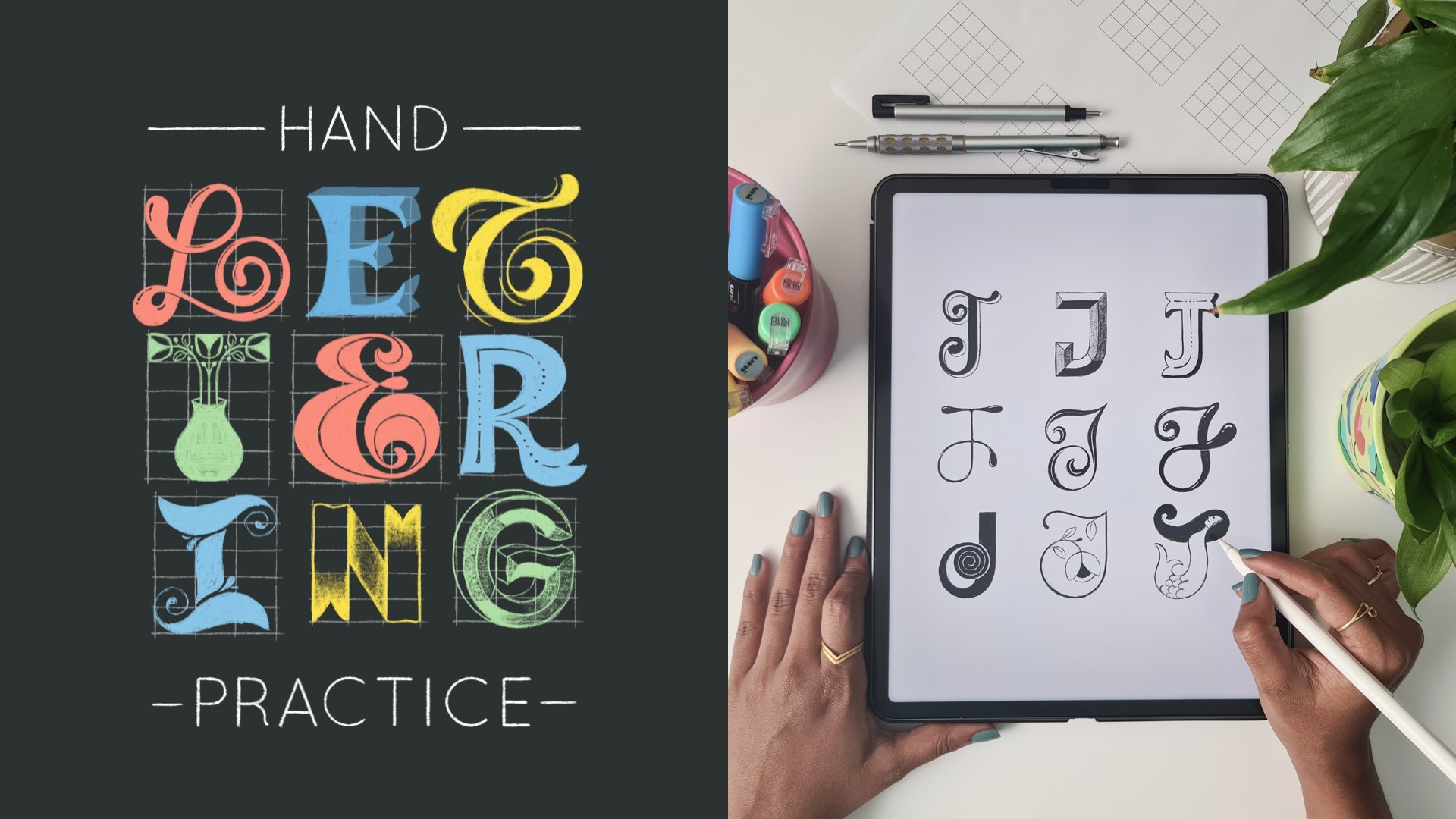
Prática de lettering à mão: 3 passos fáceis para explorar novos estilos de tipografia
As letras são como nós. Elas vêm em todos os tipos de formatos, formas e até personalidades!
E se eu dissesse que você pode desenvolver seus próprios estilos de lettering exclusivos do zero através de prática e exploração?
Neste curso, ensinarei como desenvolver estilos de lettering através de uma abordagem estruturada usando o meu processo em 3 passos para criar letras. Guiarei você por meio desses passos detalhadamente e mostrarei exatamente como uso eles para desenvolver vários estilos de uma única letra.
Tudo que você precisa fazer é usar essa fórmula que ensino para praticar e desenvolver seus próprios estilos de tipografia únicos, um caractere de cada vez.
A prática diária focada é a única coisa que levará você a um novo nível em sua jornada de lettering. Na minha opinião, não existe uma quantidade de dicas e truques que substituirá o que a prática pode fazer por suas habilidades. No entanto, pode ser difícil saber como abordar suas sessões de prática para poder aproveitá-las ao máximo. E é isso o que este curso resolve para você.
Neste curso, você aprenderá:
• O que um “estilo de lettering” realmente significa.
• Como praticar o desenvolvimento de letras em uma abordagem organizada e estruturada.
• Como dividir o desenvolvimento do seu lettering nos seguintes pequenos passos:
• Proporções
• formas
• Detalhes
• Como guias de diferentes proporções afetam os tipos de fontes e como aproveitar isso durante sua exploração.
• Melhores práticas e dicas para criar letras e números visualmente equilibrados.
Além disso, você construirá uma grande biblioteca dos seus próprios estilos de lettering que poderá consultar em projetos futuros. Ainda, você pode assistir todo o meu processo de desenvolvimento de nove variações diferentes de uma única letra do início ao fim. Será como sentar ao meu lado no meu estúdio enquanto me perco em minhas letras!
• Arquivos de modelo (disponíveis para download na seção Recursos)
Estarei demonstrando minhas técnicas desenhando no meu iPad usando o aplicativo de desenho Procreate e um Apple Pencil. No entanto, você pode me acompanhar usando qualquer meio de desenho da sua escolha — não é preciso usar um iPad para fazer este curso.
1. Introdução: [MÚSICA] As letras são como nós, elas vêm em todos os tipos de formas, tamanhos e até personalidades. E se eu dissesse que você tem a capacidade de desenvolver seus próprios estilos de letras únicos do zero para a prática e exploração. Sou Vinitha Mammen, uma artista e ilustradora de letras freelancer com formação em design de moda, e uma professora de topo no Skillshare. Nesta aula, ensino-vos a desenvolver estilos de letras por meio uma abordagem estruturada usando meu processo de três etapas de construção de letras. Vou levá-lo por essas etapas em detalhes e mostrar exatamente como as coloco para usar para desenvolver vários estilos de uma única letra. Tudo o que você precisa fazer é usar essa fórmula que eu ensino você a praticar e desenvolver seus próprios estilos de letras únicos, um personagem de cada vez. Trabalhar diariamente em direção a um objetivo específico me ajudou mais do que qualquer outra coisa na minha jornada de letras e ilustrações. Ao longo desses desafios diários, meu próprio estilo de letras único começou a se revelar de maneiras diferentes e isso me deu um senso de direção para avançar. Então, se você aceitar esse desafio, tenho certeza que ele lhe apresentará algumas revelações que mudam a vida ao longo do caminho. Ao final desta aula, você terá um método organizado e estruturado para praticar e explorar suas letras. Se você concluir seus projetos, você terá uma enorme biblioteca de referência de seus próprios estilos de letras que você pode usar em seus projetos futuros. Esta classe é para qualquer pessoa que queira aumentar o nível seu jogo de letras e é adequada para todos os níveis de habilidade. Se você é um iniciante que não sabe como começar, ou já é um artista de letras de nível intermediário ou avançado procura alguma variedade autêntica em seu estilo, eu te cobriu. Vou demonstrar minhas técnicas esboçando no meu iPad usando o aplicativo de desenho Procreate e um lápis Apple. No entanto, você pode acompanhar comigo usando qualquer meio de esboço de sua escolha. Você não precisa ter um iPad para fazer essa aula. Então você está pronto para soltar e fazer alguns exercícios de letras que mudam a vida comigo? Vamos começar. [MÚSICA] 2. Projeto do curso: [MÚSICA] Nesta aula, vamos explorar diferentes estilos de letras através da prática, então seu projeto com essa aula é exatamente isso, prática. Você vai explorar nove variações diferentes de cada letra maiúscula no alfabeto inglês e números de 0 a 9, então isso é 36 ao todo. Para isso, juntei alguns modelos de prática com guias de letras, para que você possa explorar diretamente sem ter que fazer todas as coisas chatas. Fazer todos esses 36 personagens de uma só vez será cansativo e até frustrante, então minha sugestão é que você enfrente apenas um ou um máximo de dois por dia. Dessa forma, você ficará menos sobrecarregado e poderá se aproximar de cada um com uma mente nova. Você pode usar qualquer meio com o qual você se sinta mais confortável para esboçar, você pode usar os modelos digitais para desenhar no seu iPad ou nos modelos imprimíveis, se quiser praticar tradicionalmente com caneta ou lápis em papel. Antes de seguir em frente, faça o download desses modelos de prática na seção de recursos e mantenha-os à mão. À medida que você progride em sua prática, você pode fazer upload de imagens e vídeos de suas explorações na galeria do projeto, para que todos possamos nos inspirar trabalho um do outro e nos manter e uns aos outros responsáveis. Também farei esse projeto e estarei enviando minhas folhas de prática na galeria do projeto, bem como no Instagram. Se você optar por compartilhar sua jornada de prática no Instagram, não se esqueça de me marcar em suas postagens, histórias e reais para que eu possa ver e compartilhar seu trabalho. Dito isso, eu não quero que você se preocupe em compartilhar seu trabalho enquanto explora. A pressão de compartilhar seu trabalho às vezes pode realmente atrapalhar sua solta e se isso é algo que o incomoda, e eu quero que você saiba que você absolutamente não tem que compartilhar seu trabalho. Claro, adoraríamos ver o que você inventou, mas o mais importante aqui é que você explore sem se limitar de forma alguma. Você pode muito bem terminar cada personagem e depois decidir se você quer compartilhar ou não, legal? Da mesma forma, não se preocupe alcançar linhas e curvas perfeitas toda vez ou se você estiver usando o Procreate sobre como seus ajustes afetarão seu vídeo de lapso de tempo, também você pode usar sua borracha tanto ou tão pouco quanto quiser. Tudo o que eu quero é que você deixe perder, confiar no processo e se divertir [MÚSICA], então vamos? Na próxima lição, vou orientá-lo pelo meu processo de três etapas de chegar a diferentes estilos de letras. [MÚSICA] 3. Processo de três etapas: [MÚSICA] O que exatamente queremos dizer quando dizemos estilo de letras? Existem muitos fatores diferentes que entram na definição de um estilo de letras específico. O tipo de letra, os ângulos, o humor, o peso das linhas, os elementos detalhados e muito mais. Todos eles contribuem coletivamente para um estilo de letras específico. Quando tentamos criar novos estilos, temos um monte de coisas para pensar, e se tentarmos enfrentá-los de uma só vez, estaremos por todo o lado. Em vez disso, dividimos isso em um processo simples de três etapas para que tenhamos uma abordagem mais estruturada para desenvolver estilos de letras e podemos nos concentrar em uma coisa de cada vez. Deixe-me dar um pequeno vislumbre desse processo. Primeiro, estabelecemos as proporções de nossos personagens definindo guias para desenharmos. Em segundo lugar, exploramos e chegamos às formas que formam nossas letras. Na etapa final, adicionamos detalhes para encerrá-lo. Falarei sobre cada uma dessas etapas em detalhes nas próximas lições. Por enquanto, tudo o que você precisa lembrar é proporções, formas, detalhes, nessa ordem. Na verdade, é um erro comum de novato, não apenas com letras, mas com qualquer tipo de desenho, ficar preso nos detalhes imediatamente, acabando com peças que estão fora de proporção ou falta de equilíbrio visual. Em vez disso, se você começar estabelecendo uma base sólida antes refinar as coisas e adicionar os detalhes, terá uma chance muito melhor acabar com um esboço bem equilibrado. Na próxima lição, vamos dar uma olhada boa e detalhada em nosso primeiro passo, proporções. [MÚSICA] 4. Passo 1: proporções: [MÚSICA] Como vimos na lição anterior, a primeira coisa em que nos concentramos em nosso processo de três etapas são proporções. Vamos dar uma olhada em como as proporções afetam os estilos de letras e como podemos jogar com eles para criar letras únicas. Agora, de um modo geral, a maioria das nossas letras maiúsculas e números cabem bem dentro de uma grade de cinco por três. Existem algumas exceções às quais chegaremos daqui a pouco, mas, por enquanto, vamos ver como isso funciona. Tenho uma grade de cinco por três aqui. Vamos tentar usá-lo para desenhar algo simples como um E. Com letras como essa, você só precisa seguir as diretrizes e preencher os quadrados apropriados em sua grade. É muito simples. mesmo com outras letras de linha reta como T, H e assim por diante. Agora, se você quiser fazer uma letra mais curvilínea, S , por exemplo, as partes mais arredondadas das curvas escolherão um pouco para fora das guias. Não tente encaixá-los perfeitamente dentro dos guias. Eles ficam melhores quando se estendem para fora do tad. Como você pode ver, elas não são tão diretas quanto as letras de rua, mas uma coisa que ajuda é realmente usar a grade para se concentrar em pequenas seções de cada vez. Uma vez que você pegue um jeito, não será mais um grande negócio. Pratique para chegar lá. Essa é a única maneira. Agora eu tenho as partes superior e inferior. Em seguida, conectamos os dois derrubando isso assim, trazendo isso assim. Agora só precisamos seguir essa curva e desenhar uma curva paralela para essa curva. Da mesma forma aqui, você deseja desenhar uma curva paralela a essa curva. Vamos apenas derrubar o N e depois um pouco assim e fechá-lo. Isso surge assim e, novamente, feche-o. Veja que você ainda está usando essas linhas de grade para guiar suas curvas. Só que você precisa obter suas curvas para se estender um pouco para fora da grade para obter uma forma suave e equilibrada. Quando você o coloca ao lado das outras letras, as curvas são esmagadas na grade, elas não parecerão coesas juntas. Eu vou apenas preenchê-los também para que você possa ver a forma melhor. [MÚSICA] Agora, você pode usar essa grade, não apenas para letras, mas também para números. Vamos tentar um, como sete, por exemplo. É assim que eu faria um sete com uma linha inclinada como esta e uma linha reta no topo. Muito fácil. Agora, até agora, usamos uma grade de cinco por três com colunas e linhas de igual largura. Esta e esta são a mesma largura e é mesmo por toda parte. Agora, podemos tentar mudar isso. Por exemplo, dessa forma podemos mantê-lo o mesmo, mas ao longo desse lado podemos aumentar a largura. Vamos fazer seis em vez de três. Dois, três, quatro, cinco, seis. Vou completar o retângulo. Agora, em vez de desenhar cada linha, vamos desenhar todas as outras linhas para que ainda tenhamos três colunas. É apenas duas vezes mais largo agora. Ainda são cinco por três, apenas com proporções diferentes. Agora vamos tentar usar esse cara para participar do E. O processo é exatamente o mesmo que fizemos antes. Veja, apenas variando as proporções da grade, temos uma aparência diferente E. Da mesma forma, podemos tentar todas as variações diferentes nas proporções. Por exemplo, vamos fazer um do outro lado. Em vez de cinco quadrados para baixo, faremos 10. Dessa forma, vamos voltar para apenas três. Agora nossas colunas são todas de um quadrado largura e nossas linhas terão dois quadrados de largura. Vamos desenhar nosso E nesta nova grade. [MÚSICA] Lá temos mais uma variação do E e você pode ficar ainda mais louco com isso. Vamos tentar alguma coisa. Começaremos com um retângulo de cinco por três, assim como o nosso original. Agora, em vez de dividir isso igualmente em linhas e colunas, podemos até dividi-lo de forma desigual. Em vez de desenhar uma linha no primeiro quadrado, desenhamos um pouco mais alto. Da mesma forma aqui, vamos um pouco mais baixo. Para nossa linha do meio também, podemos entrar um pouco para dentro. Esses três são quase da mesma largura e os dois intermediários são mais grossos e vamos ficar com colunas de igual largura por enquanto. Esta também é uma grade de três por cinco, mas com robôs variados. Agora vamos ver como nosso E parece nesta grade. É semelhante ao primeiro, mas ainda é um pouco diferente. Assim, você pode brincar e criar todas as variações nas proporções da grade, chegar a letras com proporções diferentes. Estou tentando outro aqui com linhas mais grossas na parte superior e inferior. Isso me dá um E que se parece com isso. Em seguida, vou começar com um quadrado aleatório como este e vamos ver o que acontece se dividirmos apenas a linha superior em duas e mantivermos as outras quatro linhas um quadrado de largura. Mais uma vez, temos cinco linhas e vou completamente aleatório com as larguras da minha coluna. Só estou experimentando aqui indo completamente aleatório. Isso é o que isso me dá. Vou tentar mais um que seja extra largo, com uma linha do meio muito magra. Foi isso que acabei usando essa grade. É aqui que a proporção realmente entra em jogo. É assim que variamos as proporções de nossas letras variando as proporções dos próprios guias. Como você pode ver, as possibilidades das diferentes proporções às quais você pode chegar são praticamente infinitas. Quero encorajá-lo a escolher qualquer letra ou número e enlouquecer tentando todas as proporções para os guias. São atividades muito satisfatórias. Tenho certeza que você vai gostar. Fato divertido, são essas proporções que essencialmente oferecem os diferentes estilos de fonte dentro de uma família de fontes, como regular, negrito, condensado, etc Agora que você sabe como isso funciona, você pode até criar seus próprios estilos do zero. Agora, lembre-se que mencionei que existem algumas exceções. Letras mais largas como M e W não se encaixam muito bem na grade cinco por três. O que eles precisam é uma grade de cinco por cinco e, em seguida eles se encaixam bem e confortáveis assim. Você pode jogar com as proporções da grade cinco por cinco, como fizemos antes, para chegar a diferentes proporções de M e W's também. Eu reuni dois tipos de modelos de prática para você. Um com apenas o básico é para uma proporção e outro com grades em uma mistura aleatória de proporções. Você pode decidir se deseja fazer todas as nove variações em apenas uma proporção, ou se deseja misturá-la com proporções aleatórias. No entanto, se você me perguntar, minha recomendação pessoal seria que você comece com apenas uma proporção, especialmente se você é um iniciante ou se você não fez um exercício semelhante antes. Dessa forma, você pode manter essa coisa constante e explorar formas e detalhes mais livremente. Em qualquer caso, você verá isso na próxima lição de demonstração que mesmo com apenas uma proporção básica, você pode criar um monte de estilos de letras únicos. Então, mais tarde, você pode progredir para fazer um conjunto com proporções mistas como um exercício de nível mais avançado. Você também é mais do que bem-vindo para criar seus próprios guias, para praticar modelos, dependendo de suas preferências pessoais. Na próxima lição, passaremos para o segundo passo, que são formas. 5. Passo 2: formas: [MÚSICA] Agora que sabemos como diferentes proporções de guias formam letras de pesos diferentes, vamos dar uma olhada nas formas. Este é o meu passo favorito, provavelmente porque é aqui que meus sucos criativos fluem mais. Uma única letra pode ser formada de várias maneiras diferentes usando diferentes tipos de formas. Dependendo das formas que formam letras, elas podem ser categorizadas em diferentes tipos, como serifas, sans serifs, roteiro, caligrafia, letra preta, exibição, etc Mas não estamos indo por esse caminho. Para os propósitos desta classe, não vamos classificar nossos estilos de letras ou tentar aprender as regras de cada estilo. Vamos deixar que nosso estado de imaginação controle e remova intuitivamente as formas de cada letra. Deixe-me mostrar o que quero dizer. Tenho aqui um E básico e a proporção mais básica da nossa lição anterior. Agora podemos começar a explorar diferentes variações de forma para isso. Por exemplo, em vez dessas linhas retas, podemos codificá-las um pouco para dentro assim [MÚSICA] e fechar as extremidades. Se desativarmos as camadas guia, é assim que parece. Nesse caso, era apenas uma pequena diferença de forma. Mas é definitivamente um estilo de letras diferente do original por causa da diferença na forma. Aqui está outro fácil. Você pode começar apenas curvando-se nos cantos assim, [MÚSICA] cobrir até os cantos internos e, em seguida, conectá-los para fechar a forma. Esse é outro e você pode deixá-lo assim ou até mesmo levá-lo mais longe. Quando eu olhar para ele agora, acho que será bom apenas empurrar essa parte para cima um pouco mais e ajustar as curvas para se misturar com a nova forma, [MÚSICA] e, da mesma forma, isso pode se mover um pouco para baixo. [MÚSICA] Essa é outra opção. Basta explorar uma coisa de cada vez, dar uma olhada e fazer algumas modificações se quiser. Também podemos nos desviar muito mais da nossa forma básica do que temos feito até agora. Vamos ver como podemos transformar isso em um estilo mais cursivo E. Para isso, vou começar desenhando algumas curvas grandes assim e depois refinando-as e fechando a forma com linhas mais curvas. Eu não estou seguindo nenhuma regra de caligrafia aqui enquanto eu libero a forma, só estou indo para ela. [MÚSICA]. Lá vamos nós. Assim, você pode criar uma grande variedade de formas de letras desviando-se tão pouco ou tanto quanto quiser da forma básica de cada letra. Você só precisa ter certeza de que os elementos fundamentais de cada letra estão intactos e que legibilidade não seja comprometida ao longo do caminho. Agora, vamos passar para nossa última etapa, que é Detalhes na próxima lição. [MÚSICA] 6. Passo 3: detalhes: [MÚSICA] Nossa última etapa neste processo é adicionar os detalhes. É aqui que adicionamos esses toques finais para elevar nossas letras. Esses são os pequenos elementos que dão às nossas cartas suas próprias personalidades únicas. Esses detalhes podem ser qualquer coisa, desde elementos sutis, como texturas ou realces e sombras, até outros mais óbvios, como efeitos 3D , sombras soltas, em linha ou conjunto de detalhes. Vamos tentar adicionar alguns detalhes ao Es que estamos explorando. Para este, vamos começar adicionando alguns detalhes simples em linha como esse, apenas nos cantos podem estar. Engrossá-los até os cantos, um pouco ou algo assim. Muito simples, mas ainda eficaz. Talvez apenas uma pequena linha como essa na barra transversal do meio e pode ser isso, ou você poderia adicionar um efeito 3D a isso. Se você quiser aprender como crio esses efeitos 3D passo a passo, ensino isso em detalhes na minha turma chamada Hand Lettering and Beyond: Negative Space 3D Lettering with Watercolors. Essa é outra opção ou você pode adicionar alguns pequenos detalhes aos fins aqui. Algo assim talvez, onde simplesmente dividimos o fim em dois, e talvez adicionamos alguns pontos para dar esse toque retro. Assim mesmo. Você pode realmente levá-lo para qualquer direção que você quiser. Vamos tentar isso com a segunda forma em que chegamos. Poderíamos fazer algo como um contorno offset. Esse processo é semelhante a fazer efeitos 3D, mas sem conectar as faces frontal e traseira entre si. É como uma superfície flutuante que se desloca ligeiramente da principal. Ou com letras em negrito como esta, é uma ótima oportunidade de soltar padrões dentro delas. Já que você tem muito espaço para preencher , então vamos tentar um padrão aleatório. Essa é outra opção divertida, ou você pode mantê-la realmente mínima simplesmente adicionando alguns círculos a essas extremidades curvilíneas para que pareçam pequenos buracos nas letras. Com essas letras que parecem curvas e fluidas, meus detalhes favoritos para adicionar sobre elas são apenas alguns destaques simples. Vou preenchê-lo completamente e depois adicionar essas bolhas brancas sobre as partes arredondadas, apenas de um lado, então parece que está refletindo a luz. Em seguida, algumas linhas de destaque finas ao redor das partes mais finas da letra também. Ou você também pode fazer um efeito 3D nessas letras curvilíneas, não apenas nas retas. A técnica permanece exatamente a mesma. É assim que uma versão 3D simples disso parece. Também podemos misturar vários detalhes juntos. Por exemplo, você pode fazer um efeito 3D, bem como um inline. Mas não exagere, mantenha um máximo de dois para que você não esteja adicionando o caos à equação. Na verdade, você pode até pular a adição de detalhes por completo. Não é um passo obrigatório. Em alguns casos, as formas são altas o suficiente para falar por si mesmas. Ou você está deliberadamente tentando manter as coisas mais simples Nesse caso, adicionar detalhes pode ser demais. Depende praticamente das preferências individuais sobre onde você desenha a linha. O que parece uma parte orgânica da carta e o que parece fora do lugar. É uma boa ideia sempre fazer check-in com você mesmo após cada detalhe que você adicionar e garantir que você sinta que deveria ser. É isso, agora você conhece todas as três etapas do nosso processo. Na próxima lição, juntarei tudo isso e mostrarei um exemplo de como eu faria esse exercício de exploração do início ao fim. 7. Demonstração do projeto: parte 1: [MÚSICA] Damos uma boa olhada em nosso processo passo a passo e agora estamos prontos para realmente aplicar esse processo para praticar o desenvolvimento de novos estilos de letras. Escolherei a letra J para demonstrar a você como eu faria esse exercício. Vamos direto a isso. uma tela quadrada aberta aqui no meu aplicativo Procreate. Você pode ir com o tamanho que quiser. Esta é uma tela quadrada de 12 por 12 polegadas. Agora vamos trazer o modelo para isso. Vamos aqui para este ícone de chave inglesa. Vá para Adicionar, insira uma foto e seus modelos baixados devem estar aqui. Então toque nele. Se o modelo não preencher totalmente a tela, basta redimensioná-la. Certifique-se de que a magnetics e o encaixe estejam ativados. Basta arrastar essas alças para resnap até as bordas da tela. O mesmo deste lado e solte. É isso. Nosso guia agora está pronto. Você pode entrar no painel Camadas e tocar neste final aqui. Você pode reduzir a opacidade de suas diretrizes, se quiser. Normalmente eu faria isso, mas não estou agora para que você possa ver os guias com clareza suficiente. Tudo bem, então vamos começar com nossas explorações com a letra J. Vamos abrir uma nova camada, onde começaremos com nosso esboço. Primeiro, estou apenas usando meu guia para desenhar um J. muito básico Estou usando o pincel de lápis 6B, que é um pincel Procreate padrão na categoria de esboço, você pode usar qualquer pincel que estiver confortável usando, e você pode usar a cor que quiser. Gosto de esboçar com azul. Agora a partir daqui, ele vai se curvar. Olhe para este quadrado sozinho por um momento, deste canto para este canto, que eu vou curvar exatamente assim. Em seguida, estenda-o. Da mesma forma paralela a essa curva. Nós desenhamos uma curva menor aqui assim. Em seguida, vamos fechar o site e preenchê-lo. Essa é a sua J. básica Uma coisa que você pode fazer é, se você quiser que essa forma básica passe o mouse abaixo de seus esboços, você pode fazer isso. Basta ir aqui, deslizar para a esquerda nesta camada, tocar em duplicatas para fazer cópias dela e, em seguida, você pode arrastá-lo para todos os seus guias. Você também pode apertar esses três juntos para mesclá-los e depois duplicá-los. Então você pode movê-los juntos assim. Duplique mais uma vez e coloque-o aqui. Em seguida, você pode mesclar todas essas camadas e reduzir a opacidade dessa camada. É só lá para você ver que essa é a forma básica que estamos tentando evoluir. Se você está trabalhando tradicionalmente e não no iPad, você pode fazer isso com um marcador de cor clara e funcionará praticamente da mesma maneira. Você pode até pular esse passo completamente, se quiser, e simplesmente pular direto para explorar. Abriremos uma nova camada e chegaremos ao nosso esboço real. O que quer que saia do topo da sua cabeça, basta ir em frente. Seja qual for. Neste momento, sinto vontade de curvar esta barra superior. Então é isso que vou fazer. Apenas uma simples linha curva como essa. Então vou tirá-lo de lá assim. Quero trazer a curva para fora assim e juntá-la a essa linha. Veja como não estou deixando a forma por baixo me restringir. É apenas uma forma muito genérica por baixo. Para me lembrar com o que estou brincando aqui. Vou fazer um pequeno redemoinho aqui, e um menor aqui. Parece um pouco demais. Talvez não. Vou deixá-lo assim por enquanto. Você pode fazer todos os ajustes que deseja fazer. Ninguém vai julgar você ou questioná-lo, este é o seu exercício de prática. Apenas sinta-se livre para cometer erros. Corrija-os ou não. Eu tenho um esqueleto básico agora. Vou fazer isso um pouco mais a seguir, estou engrossando as descidas, seguindo o princípio mais básico da caligrafia, que é que os golpes estou engrossando as descidas, seguindo o princípio mais básico da caligrafia, altos são finos, e os downstrokes são grossos. Se você não tem ideia do que estou falando, confira minha aula do Skillshare intitulada letras manuais e além. Onde eu explico isso em detalhes. Eu quero que os movimentos ascendentes também sejam um pouco mais grossos, mas ainda consideravelmente mais finos do que os downstrokes. Assim mesmo. Estou expelindo a forma da minha carta. Quero que o fim disso seja assim. Bom e redondo. vez aqui, um fim bulboso semelhante. Então vou deixar as partes finas um pouco mais grossas e trazê-las aqui. Vou engrossar este de cima. Então acabe com isso assim. Isso parece bom até agora. Agora, para ter uma noção melhor de como isso parece e limpá-lo um pouco. Você pode pressionar longamente a ferramenta de borracha para apagar usando o mesmo pincel com o qual você está desenhando, e vamos nos livrar de algumas dessas linhas extras. Só estou alternando entre o pincel e a borracha para limpar minhas formas um pouco. Isso é mais sobre ver a forma mais claramente do que qualquer outra coisa, que possamos ver se precisamos fazer mais ajustes. Agora parece um pouco desequilibrado para mim. Isso é um pouco alto deste lado e o topo disso, para combinar com isso, vou apenas pegá-lo daqui e levantá-lo daqui. Então junte-se a ele de volta a isso. Agora podemos apagar tudo isso e redesenhá-lo. Acho que parece melhor, definitivamente mais equilibrado. Tudo bem, então agora a forma está pronta e podemos chegar aos detalhes. Estou pensando em adicionar um efeito 3D a este. Para isso, vou duplicar essa camada e movê-la para onde você quiser que a superfície 3D esteja. Vou reduzir a opacidade dessa nova cópia que fizemos e, em uma nova camada, podemos desenhar sobre isso para obter nossas superfícies 3D. Estamos apenas rastreando essas linhas e depois conectando-as à face frontal existente da nossa carta. Se você quiser saber como eu crio esses efeitos 3D de maneira passo a passo. Vou ensinar isso em detalhes na minha turma chamada letras à mão e além, letras 3D de espaço negativo com aquarelas. É isso. Agora podemos desligar essa camada guia. É isso. Se você quiser, você pode até preencher um deles para tornar o efeito 3D mais óbvio. Aqui estou preenchendo a face frontal da carta. [MÚSICA] Esse é o nosso primeiro. Vamos passar para o próximo. Agora, você pode continuar na mesma camada, se quiser, ou se seu iPad oferecer camadas suficientes, você pode fazer cada versão e uma nova camada, que é o que vou fazer. Agora, para o meu segundo, vou tomar essa forma básica e curvar um pouco. Da mesma forma, vou curvar este top também. Mais uma vez, esta linha. Só estou experimentando. Nunca fiz um J como este. Estou apenas experimentando, que é o que se trata esse exercício de qualquer maneira. Talvez eu acabe com isso em uma curva como essa. Isso pode ser mais direto. Vamos ver. Acho estranho agora ser honesto. Ainda não estou muito feliz com a forma, mas vou ver se há algo que eu possa fazer para melhorá-la. Talvez os detalhes ajudem. Que tal alguns detalhes do bisel? Vamos tentar isso. Vou apenas fazer um embutido básico primeiro, assim como o conectado a esses pontos. Daqui para aqui. Também aqui e aqui. Agora, parece melhor, eu acho. Vou fazer um pouco de sombreamento para fazer a caixa de aparência em relevo e muito mais. Isso é feito. Parece muito melhor. Vamos deixar isso e seguir em frente para o próximo. Abra uma nova camada e o que podemos fazer agora? Que tal tentarmos um conjunto do mesmo. Vou começar por desenhar os lados aqui e estendê-los para baixo um pouco. Em algum lugar agora você começará a se sentir solto um pouco. Inicialmente, você provavelmente teria se sentido um pouco perdido. Mas quanto mais você fizer isso, mais ideias você terá e mais fluxo você terá . Talvez assim. Nós apenas seguiremos principalmente a forma básica de nossos fantasmas de J abaixo. Vamos estender isso também e conectá-lo assim. Parece uma boa forma para começar. Agora, eu quero torná-lo mais interessante dividindo essas configurações em como um rabo de peixe. Aqui também fará a mesma coisa assim. Em seguida, apague todos esses pedaços extras. Acho que quero estender isso um pouco mais no topo. Aqui também, quero trazer isso para fora um pouco. Sim, eu gosto disso. Na verdade. Sim, eu gosto de como parece aqui, mas aqui em cima, talvez o mais curto seja melhor. Voltarei a como foi inicialmente. Como eu disse, vou deixar isso, estendê-lo um pouco. Agora, para isso, acho que um bom e divertido detalhe em linha seria bom. Primeiro vou desenhar uma luz em linha como guia. Em uma nova camada, farei o detalhe real em linha, apenas um pouco grosso e escuro do lado de fora e afunilado para dentro, e alguns pontos entre os dois. Da mesma forma aqui e aqui. Então, novamente, alguns pontos no meio. Então eu vou apagar o guia embutido que fizemos. [MÚSICA] Isso parece bom para mim. Na próxima lição, continuaremos este exercício fazendo as próximas três versões. 8. Demonstração do projeto: parte 2: [MÚSICA] Para este, eu quero experimentar um tipo monolina mais magro de J. Vou começar desenhando uma estrutura J básica. Quero fazer com que venha assim, e quero levá-lo para o outro lado assim. Talvez curve um pouco mais assim. [RUÍDO] Vou refinar um pouco essas curvas, alternando entre minhas ferramentas de pincel e borracha mais uma vez. Então, que tal algo assim? Apenas nas extremidades, apenas alguns detalhes bulbosos como este, e outro como este no final. Vou preenchê-lo e ver como isso parece. Gosto disso. [MÚSICA] Eu acho que as linhas podem precisar ser um pouco mais grossas por toda parte. Talvez possamos tornar essas articulações mais curvas e fluidas e ver como isso parece em vez dos cantos afiados. Eu gosto disso, então vou fazer isso com esse cruzamento também. Isso está me dando toda uma vibração de estrutura metálica. Todo o sombreamento que eu quero fazer são alguns destaques nessas partes arredondadas, e talvez pequenos bem nas articulações, e talvez alguns aqui, e voila. Vamos passar para o próximo. Este, vou começar com um bom estilo cursivo curvilíneo J. Se você notar, eu não estou seguindo a forma de fantasma embaixo do T. Por exemplo, eu mudei um pouco a descida para o lado, então sinta-se à vontade para fazer isso. Vou fazer uma bela cauda giratória aqui, assim mesmo. Acho que vou curvar essa parte superior um pouco mais. Agora, vou adicionar um pouco de carne a algumas partes como esta de ambos os lados de nossas linhas, misturar isso nesta curva aqui, mantendo essa parte fina e terminando a curva assim. Então talvez essa parte possa ser assim. Estou apenas experimentando aleatoriamente as coisas com base em onde há espaço. Como aqui, não há muito espaço, então eu não quero engrossar nessa área. Vou ver onde posso encaixar uma espessura extra graciosamente sem que pareça abafada. Acho que talvez apenas um lado seja suficiente neste caso. Deixe-me tentar levantar esse lado. Sim, acho que gosto disso. Parece interessante para mim. Talvez, por aqui, nos livremos do interior. Aqui vamos torná-lo semelhante a isso, assim, [MÚSICA] e misturá-lo na curva. Bom. Vou preencher rapidamente essas formas. Quanto aos detalhes sobre isso, acho que vou fazer algo assim. Sim, alguns detalhes espaciais negativos. Apenas começando do lado de fora da forma e terminando casualmente por dentro. [MÚSICA] Isso pode ser feito. Agora, para o nosso próximo, eu gostaria de tentar algo com a mesma forma básica, então eu quero apenas duplicar isso e movê-lo para cá assim e mantê-lo lá com um baixo nível de opacidade. Posso seguir essa forma novamente em uma nova rede. [MÚSICA] Apenas uma forma básica. Agora, aqui, vou fazer com que venha assim, e depois assim, como um estilo de roteiro mais tradicional, e essa parte exatamente assim. Agora posso ir em frente e excluir essa camada guia extra, pois isso é tudo o que eu quero tirar disso. Só vou engrossar os golpes com formas mais arredondadas desta vez. Engrosse os topos altos também um pouquinho e termine com uma lâmpada arredondada grossa e, da mesma forma, aqui também. [MÚSICA] Não se preocupe que esses dois estilos pareçam muito semelhantes e estejam bem ao lado do outro. Está tudo perfeitamente bem. Na verdade, eles provavelmente não estarão próximos um do outro quando você realmente usa esses estilos em seus projetos, então por que isso deveria importar? Apenas lembre-se de que este não é o fim. Este é apenas um meio de descobrir novas ideias e deixá-las evoluir. Não quebre o fluxo de suas ideias surgindo deixando essas coisas o incomodarem. Está perfeitamente bem. Exatamente o que vier à sua cabeça, faça com que esse pensamento flua para sua mão e para o papel ou tela neste caso. Apenas tire tudo da sua cabeça e na sua frente. Dessa forma, você abre espaço para novas ideias e descobertas. Aqui eu quero que a travessia seja claramente visível, então vou apagar um pouquinho disso. Isso parece tão fluído e suculento agora. Quero fazer alguns destaques para que pareça algumas letras líquidas brilhantes. [MÚSICA] Farei um aqui também para destacar esse cruzamento um pouco mais, e podemos chamar isso de feito. A próxima lição será nossa terceira e última parte deste exercício. Vejo você lá. 9. Demonstração do projeto: parte 3: Para nossa sétima variação no Jape, vou começar com um visual monolina bonito e ousado. Vou mudar a linha descendente para o lado, depois colocá-la para baixo para uma curva. Às vezes, são necessários alguns ajustes para misturar curvas suavemente em linhas retas. Isso está vindo assim, eu quero que isso venha por cima desta linha e eu vou desenhar um círculo completo aqui, e misturá-lo na curva. Parece muito confuso neste momento, não é? Tudo bem. Dado o objetivo do nosso exercício, isso não importa, especialmente nesta fase, quando eles ainda descobrem isso. Mais tarde, você pode limpá-lo se quiser. Isso é assim, e eu tenho essa parte circular chegando sobre ela. Vou limpar algumas dessas linhas de distração para que eu tenha uma melhor noção da forma. Vamos ver. Na verdade, esse pouco não será visível. Talvez não precisemos da barra transversal superior. Vamos ver o que acontece se nos livrarmos disso. Isso pode ser tudo o que precisamos. Ainda é um J, assim? Sim, por que não, então vamos mantê-lo assim. Vou desenhar essa linha novamente, possamos direcionar o resto dessa curva corretamente e então podemos apagá-la novamente. Porque este é um processo de ida e volta, como você pode ver, não um linear onde simplesmente vamos do ponto A ao ponto B. Estamos apenas tentando construir essa transição entre o espesso descida e o curso superior fino gradualmente. Novamente, muitas linhas de distração, então vou me livrar de algumas delas, e estou refinando as curvas um pouco mais. Vamos preenchê-lo. Agora aqui, quero que a parte circular seja claramente visível sobre a linha grossa. Vou dar a volta ao círculo e deixar de fora um espaço negativo fino para defini-lo apenas na parte que se cruzam. Em seguida, continuamos preenchendo, fazendo mais alguns ajustes para definir bem as formas. Agora, para os detalhes, talvez uma espiral dentro do círculo, assim. Gosto disso. Mas vou fazer um mais limpo. Tire um pouco de tempo para refinar as curvas enquanto eu vou. Se você notar, eu continuo inclinando muito minhas câmeras durante meu processo de esboço, e isso é para que eu esteja desenhando cada curva em um ângulo que me parece mais natural, o que realmente me ajuda a obter curvas mais suaves. Isso é algo que eu adoro em desenhar no iPad. É tão fácil ajustar o ângulo de desenho à medida que você desenha. Tudo bem, lá temos isso. Acho que não precisamos de mais detalhes sobre isso. Vamos passar para o próximo. Se você viu meu trabalho, sabe que eu amo meus florais, então como não posso fazer uma versão floral? Acho que vou usar essa forma em si mesmo e fazer algum design floral e, por favor, o círculo talvez. Vamos tentar. Novamente, faço uma cópia disso e movê-lo para cá, reduzo a opacidade e, em uma nova camada, vou desenhar sobre essa forma. Começarei com um círculo desta vez, desenhando um círculo áspero como este, pressione e segure, e toque com um dedo para obter um círculo perfeito. Agora vou desenhar em torno do G assim. É isso. Agora vou excluir essa camada guia. Estou abrindo uma nova camada e usando isso como meu novo guia, e vou fazer alguma flor aqui. Talvez algo assim, eu não sei, estou apenas tentando algo. Vamos ver com o que acabamos. Teremos esse formulário em pétalas como esta. Tenho uma aula completa sobre desenvolvimento dessas ilustrações florais estilizadas. Então, se você quiser aprender a fazer isso, definitivamente confira isso. Gosto de como isso parece até agora. Agora, eu quero que esse caule saia mais perpendicularmente em relação à flor em oposição à linha tangencial que o guia está formando. Então, algo assim. Então nós o misturamos na forma guia, assim. Vou refinar essas curvas um pouco mais para torná-las mais suaves. Acho que quero adicionar uma boa barra superior curvilínea nisso, então temos mais hastes para adicionar mais elementos florais. Gosto disso. Vamos adicionar uma folha aqui, talvez outra aqui, e mais uma aqui, um pequeno broto aqui. Podemos usar essa mesma forma no final aqui. Há mais espaço aqui, então talvez um aqui também. Na verdade, talvez não precisemos deste, só que isso serve. Sim, parece melhor. Estou me perguntando, e se derrubarmos isso um pouco? Basta selecionar à mão livre em torno dele e arrastá-lo para baixo um pouco. Talvez em algum lugar por aqui. Isso parece muito mais equilibrado. Havia muito espaço vazio na parte inferior e estava ficando um pouco lotado por cima, então agora vou suavizar isso, e vou engrossar o caule todo um pouco e preencher a parte central apenas para trazer algum contraste com a flor. Isso veio disso, mas parece tão diferente no final. Adoro, apesar de como parece simples. Sinto que tudo aqui parece que era para não ser forçado lá, e esse é o melhor design na minha opinião. Agora vamos fazer nosso último. Você também pode levar algum tempo para olhar a forma e explorar o que você vê. Como agora eu vejo a curva do J sendo algum tipo de cauda, como um rabo de peixe talvez. Vamos explorar isso e ver onde isso nos leva. Vou começar com a cauda em si, assim. Agora, podemos dar ao nosso peixe um golpe assim. Não sei. Não acho que isso esteja funcionando. Na verdade, podemos fazer uma sereia em vez de um peixe. Apenas moldando um corpo para ela, e uma bela cabeça redonda. Talvez não seja tão redondo. Vou deixar o pescoço um pouco mais fino, e fazer um rosto um pouco mais pontudo assim, talvez. Dê-lhe um pouco de cabelo, um lindo bob talvez, agora para alguns braços. Isso parece mais um y do que um j, e isso é um grande não. Não podemos ter nossas letras parecidas com outras letras. Porque então estamos mexendo com legibilidade. A única regra inquebrável em letras para mim é esta, não comprometa a legibilidade. Eu me livrei dos braços. Ela pode ficar sem braços, tudo bem. E se fizermos o cabelo vir mais para este lado, assim, e da barra transversal superior do j? Gosto dessa direção. Vou explorar isso um pouco mais, talvez enrole até o final, assim, traga algum capricho e refinar um pouco essas curvas. Vamos dar a ela algumas características faciais simples. Talvez alguns detalhes mais bonitos e mais arredondados em vez disso. Adicione algumas escalas por aqui. Vou reduzir um pouco o tamanho da coisa toda para que ela se encaixe melhor em nossa grade, e então eu vou preencher o quadril. Nesse caso, o que você está desenhando por si só impulsiona os detalhes. Esta é uma sereia, então fazemos detalhes de sereia. Mas cabe a você decidir até onde você quer levá-lo. Por exemplo, você pode fazer escalas por todo o corpo, se quiser, você pode até rabiscar alguns padrões intrincados na balança, ou talvez dar-lhe uma roupa extravagante e algum cabelo acessórios, tudo depende de você. Estou apenas definindo o rosto um pouco mais e adicionando um fio de cabelo solto aqui para enquadrar seu rosto, e então eu vou limpar todas as linhas um pouco. Gosto disso. Agora, temos todas as nove variações do nosso j feitas. Agora, normalmente neste momento, vou dar a todos uma olhada final para ver como tudo se juntou e ver se preciso fazer mais ajustes. Sempre haverá algumas versões favoritas e algumas versões menos favoritas. Isso é totalmente normal. Você não precisa gostar deles todos com a mesma intensidade. No entanto, se você tem algo que você realmente não gosta, e se você tiver outras ideias flutuando em sua cabeça, volte lá e dê outra chance. Nada é colocado em pedra. Por exemplo, agora olhando para isso, acho isso estranho. Parece até um T cru. Vou tentar fazer uma forma diferente mas manter o elemento chanfro. Vou desligar a visibilidade nessa camada, abrir uma nova camada logo acima dela e desenhar uma forma mais simples como esta. Curve-o aqui. Poderia até subir daqui assim. Mais cantos são bons para essas letras estilo chanfros de fato. Quanto mais cantos tivermos, mais oportunidade de adicionar os detalhes do bisel. Agora, assim como fizemos antes, desenhamos um simples embutido dentro da forma, podemos conectar os cantos assim para nos ajudar no processo. Novamente, aqui, se fizermos isso, sabemos exatamente onde o inline muda de direção e, em seguida, basta conectar todos os cantos aqui assim e assim. Também podemos dividi-lo assim e a parte mais arredondada da curva. Agora, tempo de sombreamento, estou imaginando uma fonte de luz no topo, então as fases inferiores serão as mais escuras, a fase superior é a mais leve e tudo o mais estará no meio. Sim, eu gosto muito mais disso. Agora, vou fazer uma última coisa. Sinto que este precisa de algo mais. Acho que posso adicionar um efeito 3D também a ele. Dupliquei isso e estou movendo para uma nova posição, reduzindo a opacidade. Volte para a camada original e conecte as duas superfícies. Agora trace as linhas assim, e eu também vou preenchê-lo assim como eu vou. Agora posso excluir esse guia, apenas limpá-lo um pouco e chamá-lo de pronto. Sim, muito melhor, eu acho. Agora, você pode se livrar da camada fantasma e exportá-la assim com as guias visíveis ou você também pode se livrar da camada guia. Quanto a mim, gosto de dar mais um passo. Gosto de esboçar com uma cor azul, mas gosto que meus esboços acabados sejam em preto ou cinza escuro. Infelizmente, com o Procreate, temos uma maneira rápida e fácil de fazer isso. Selecione qualquer camada, toque em “Bloqueio Alfa”, selecione uma nova cor que você deseja, neste caso, é cinza escuro e, em seguida, toque na camada novamente e faça filé. Agora, vou fazer isso com todos eles. Se você está se perguntando como isso funciona, tenho uma lição inteira dedicada a explicar os diferentes tipos de opções de mascaramento no Procreate, incluindo este Alpha Lock no meu floral Procreate aula de ilustração , então confira isso. São todas as nove versões feitas. Isso é um envoltório sobre isso. Claro, podemos continuar para sempre, porque, como você pode ver, há tantas direções diferentes que você pode levá-las e tantas possibilidades diferentes. Mas temos que parar em algum momento. Mas veja como, apesar de termos usado nossos guias mais simples e as proporções mais básicas, acabamos com uma grande variedade de estilos de letras. Alguns deles são muito excitantes, mesmo. Se houve uma vantagem importante de toda a pesquisa que fiz durante meu mestrado em design de moda é que as restrições são boas. As descobertas mais emocionantes são feitas quando você mantém uma coisa constante enquanto muda outras, em vez de tentar variar tudo de uma só vez. Isso se aplica à nossa prática de letras também. Por todos os meios, experimente proporções diferentes também, mas talvez dê a si mesmo outra restrição quando você pensa nisso. Dessa forma, você tem algo para mantê-lo encaminhado enquanto explora. Agora, é a sua vez. Na verdade, é a nossa vez porque, como eu disse, também vou me juntar a você nesta jornada de A a Z e 0-9, então fique de olho na galeria do projeto, bem como no Instagram, se você quiser para seguir minha prática. Claro, estarei ansiosamente esperando para ver seus projetos também. Vejo você na próxima lição com alguns pensamentos finais antes de encerrarmos a aula. 10. Considerações finais: [MÚSICA] Se você explorou até uma letra usando nosso formato de exercício, estou tão orgulhoso de você. Se você fez todos os 36, então você é um superstar absoluto. Espero que você tenha descoberto algo novo e excitante nesta aula, e você o use para continuar aprimorando suas habilidades de letras. Minha sugestão é que você faça todo esse exercício pelo menos uma vez por ano e segure suas folhas de prática, sejam elas digitais ou em papel para que, um, você tenha toda essa biblioteca de referência de seus próprios estilos de letras para usar em seus projetos futuros, e dois, você pode olhar para trás e ver como suas habilidades cresceram ao longo do tempo. Estou muito animado para ver todas as diferentes formas criativas pelas quais você aplicará o que aprendeu comigo nesta aula. Pessoalmente, minha maneira favorita de levar esses esboços mais longe é criar esse tipo de composições de estilo misto onde cada letra é feita em um estilo diferente. Se você se sentir bem, escolha uma palavra e faça uma delas, ou melhor ainda, faça um pôster com suas versões favoritas de todo o alfabeto. Conecte-se comigo no Instagram e não se esqueça de me marcar em suas postagens quando você compartilha seus exercícios de letras. Eu ficaria muito feliz em compartilhar projetos de alunos por meio de minhas histórias e manter contato com você. Também compartilho vídeos de processo e bastidores de meus projetos freelance no Insta, então siga-me se quiser marcar na minha jornada. Se você gostou desta aula, considere deixar um comentário e me dar um grito nas mídias sociais porque seus comentários e recomendações pessoais ajudam massivamente minha classe a ser descoberta por novos alunos. [MÚSICA] Tenho mais letras e aulas do Procreate no Skillshare, então confira e clique no botão Seguir na minha página de perfil do Skillshare para ser notificado imediatamente quando eu publicar uma nova classe. Muito obrigado por ficar por aqui. Até a próxima vez. Tchau. [MÚSICA]